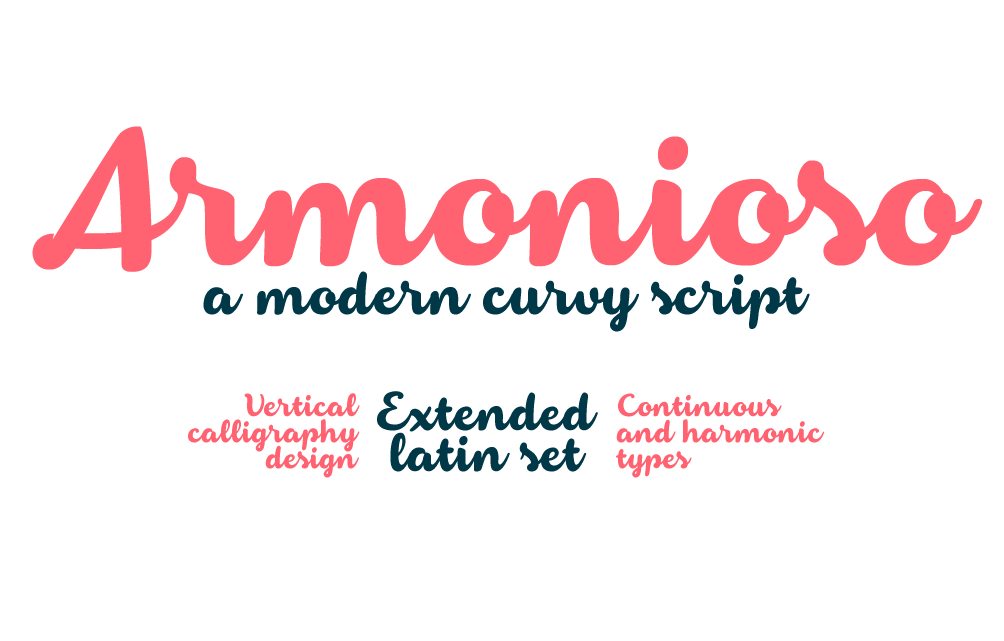
A Armonioso é uma família de tipo com traços modernos e curvados, criada por Cosimo Lorenzo Pancini. Essa tipografia traz uma atmosfera leve e fluida, perfeita para ambientes que valorizam a elegância e a sofisticação contemporânea. Na categoria de Brush Fonts, onde o design contínuo é interpretado com gestos livres e expressivos, Armonioso oferece uma versão única que combina suavidade e energia em um só tipo. Com sua tipografia fluida e curvilínea, a Armonioso se destaca em ambientes que buscam uma harmonia entre design moderno e elegância clássica. Especialmente adequada para nomes de marcas, logotipos ou elementos visuais que precisam ser leves e sofisticados, a Armonioso é um recurso gráfico perfeito para designers em busca de uma fonte diferente e única no mercado.